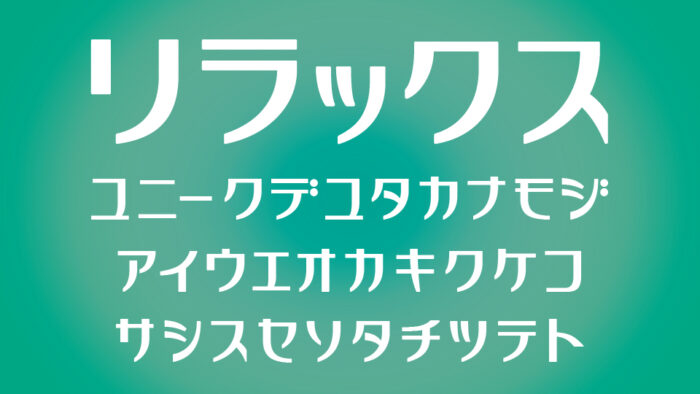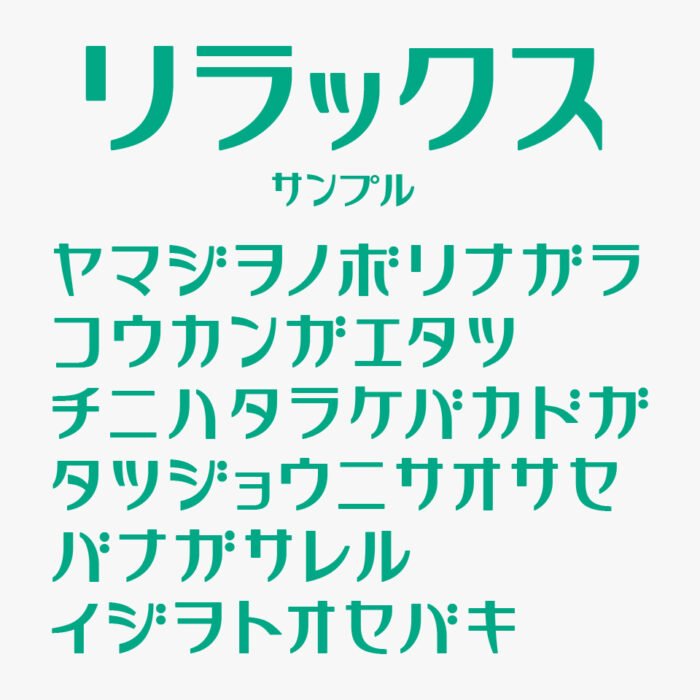
リラックスフォントは、すっきりとした線と適度な丸みを持つ、読みやすさを重視したデザイン系カタカナフォントです。
すっきり爽やかな清潔感があり、硬さを感じさせないため、安心感や柔らかさを感じるデザインです。直線的なシンプルさにわずかなカーブが加わることで、窮屈さがなく、心地よい空気感がまさにリラックス感のあるフォントです。
リラックス
収録文字は、カタカナが収録されています。
ひらがな×
カタカナ○
漢字×
リラックス